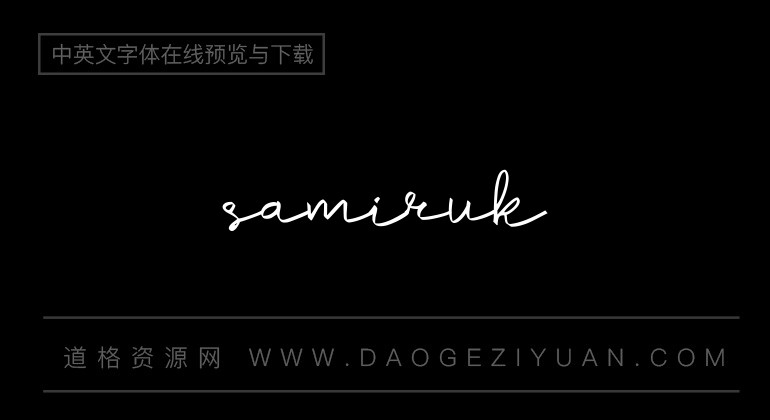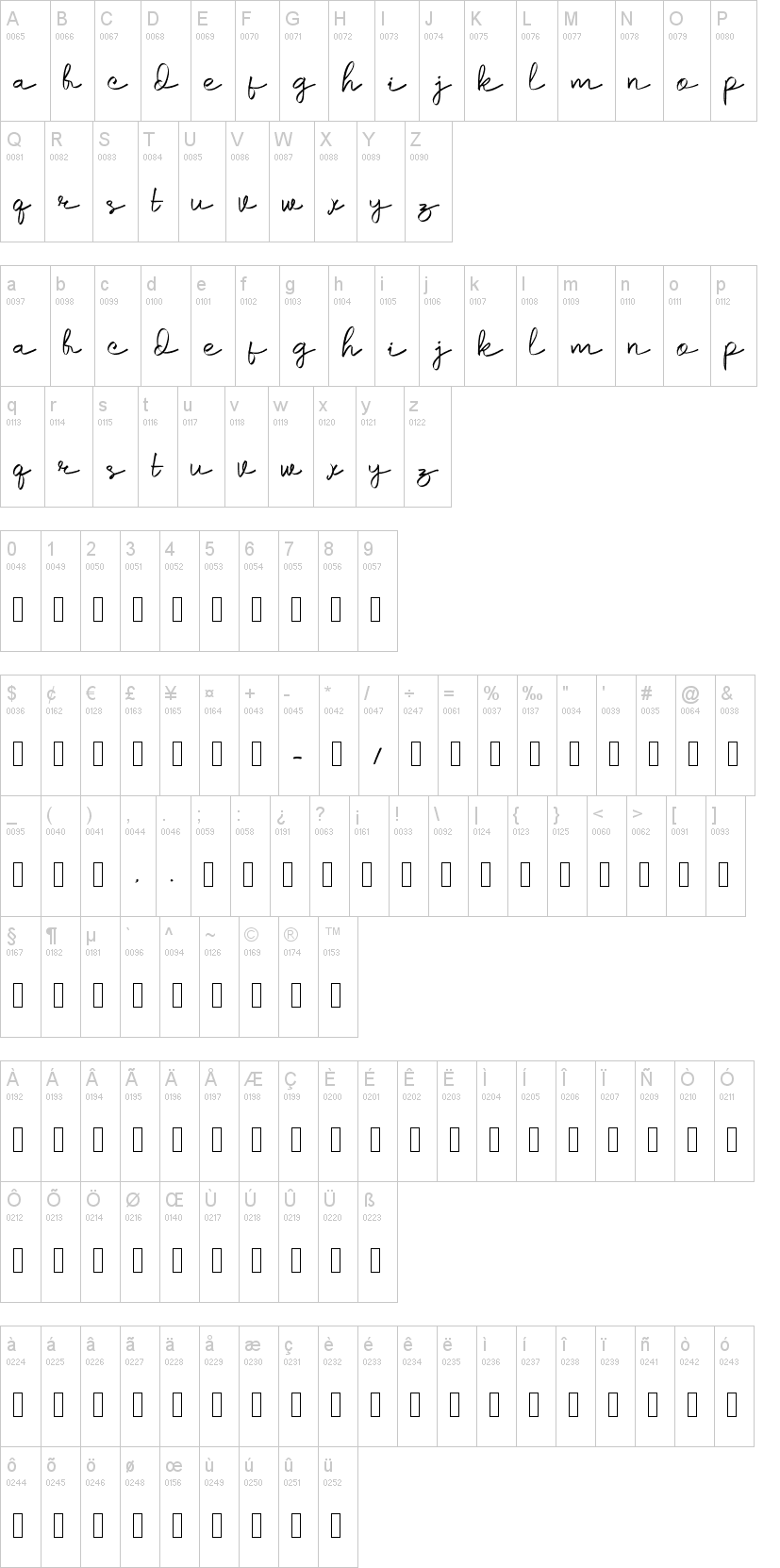
Samiruk
Samiruk字体是一款由拉丁美洲设计师Samir Al-Rukn创作的拉丁文字体。它是一种现代字体,具有优秀的细节和流畅的线条,可以轻松地搭配任何设计风格,适用于各种标识、标题、广告、印刷品等。Samiruk字体具有独特的拉丁美洲风格,可以帮助人们更好地理解拉丁文字,并为拉丁文文化增添魅力。
Samiruk是一款非常不错的手写艺术字体,具有很好的视觉感,适合于文化类的宣传设计、商业类品牌的广告和产品包装设计以及个性化文字排版等较多场景。
Samiruk字符映射图